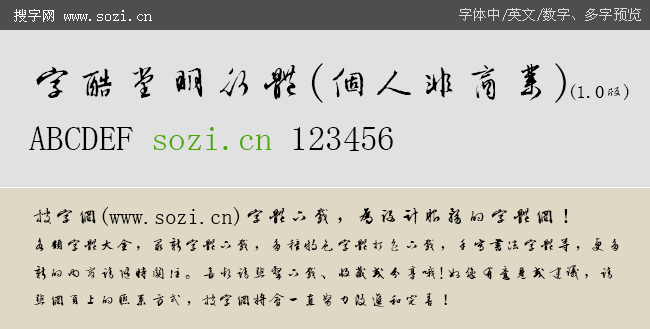
字酷堂明行體(個(gè)人非商業(yè))
搜字網(wǎng)提供一款字酷堂明行體(個(gè)人非商業(yè))中文書法字體下載,字酷堂明行體是一款非常漂亮的行書書法字體,字體飄逸大方,結(jié)構(gòu)合理沉穩(wěn),整體字形非常大氣,適合應(yīng)用于廣告設(shè)計(jì)、名片設(shè)計(jì)、包裝印刷、海報(bào)設(shè)計(jì)等應(yīng)用。